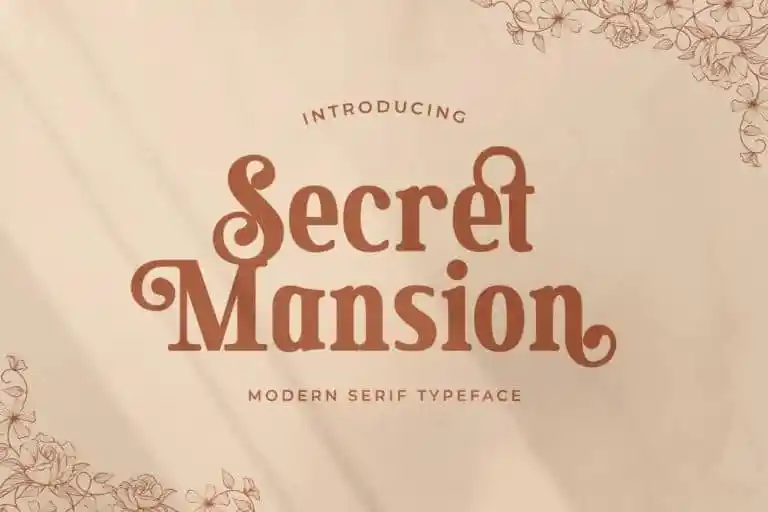
Secret Mansion Serif Font – Fonte Grátis
Secret Mansion Serif Font
A Secret Mansion Serif Font é uma escolha perfeita para projetos que valorizam estilo clássico e elegância contemporânea. Com seu desenho serífero moderno, a fonte oferece alternativas únicas que se misturam de forma suave e equilibrada, criando um design de letra irresistivelmente atraente. Além disso, o design fornece muitas variantes de ligaturas para estilos, tornando suas letras ainda mais impressionantes. A fonte foi cuidadosamente elaborada em uma delicada harmonia que pode ser facilmente combinada com um vasto número de projetos. Ideal tanto para desenhos detalhados quanto para design gráfico em alta velocidade, a Secret Mansion permite criar uma aparência refinada e sofisticada, enquanto mantém uma versatilidade extremamente valiosa. Seja em cartazes publicitários ou em trabalhos de design editorial, essa fonte se encaixa perfeitamente em qualquer projeto que valorize um toque clássico com uma expressão moderna e atemporal.